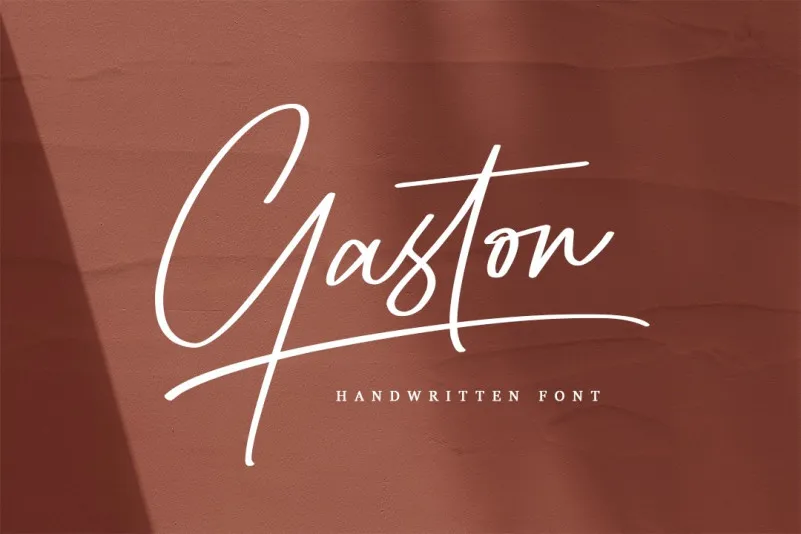
A fonte ‘Gaston Font’ é uma elegante escolha para designers que buscam criar projetos criativos com estilo. Desenvolvida pelo Moove Studio, ela destaca-se por sua tipografia script, marcada pela contraste forte entre os traços e um design clean, proporcionando caracteres alegres e divertidos. Este font inclui uma grande variedade de grafismos e ligaturas que podem ser facilmente acessados por meio do PUA encoding. A ‘Gaston Font’ não apenas enriquece qualquer projeto gráfico, mas também adiciona um brilho sofisticado à sua arte. Ideal para designers que querem dar um toque único em seus projetos de design digital ou impressão.